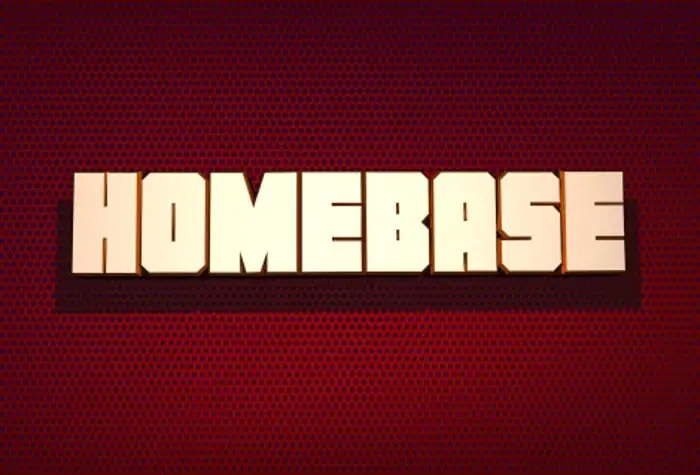
A Homebase Display Font oferece uma vasta gama de opções para personalizar qualquer projeto digital ou impresso. Com 32 versões diferentes, incluindo Regular, Italic e suas variações estilizadas como Super-Italic e 3D, ela atende a diversos requisitos designísticos. Além disso, oferece opções mais específicas para formatos especiais, como Laser, Low Laser e Duo-Laser, que adicionarão um toque único à sua identidade visual. A Homebase também inclui versões com estilos alternativos, como Outline Italic e Gradient Italic, para aqueles que buscam uma aparição diferente da fonte. Esta extensa variedade de Homebase Display Font é perfeita para designers que desejam aprimorar suas criações em um amplo espectro de aplicabilidades, desde o design digital até as impressões em papel mais elaboradas.